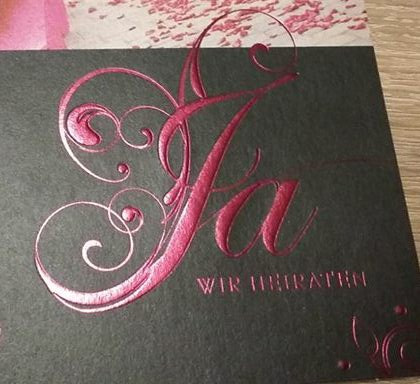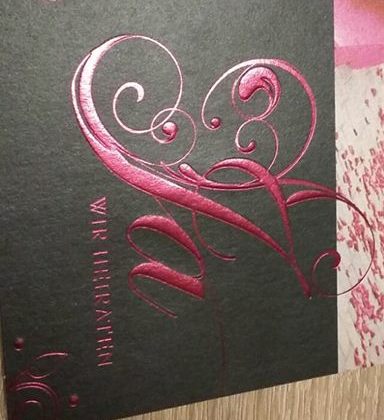
Welche Schrift? (ja, wir heiraten)
könnt Ihr mir bitte helfen, welche Schriftart dies ist.
Habe schon etliche Schriften durch, aber komme einfach nicht dahinter, wie diese Schrift heißt
Das J muss keiner Satzschrift entspringen, möglicherweise ist es auch als Zierbuchstabe für die Heißfolienprägung gestochen worden.
Kritik ist aber doch angesagt, und hier liegt das Problem in der Druckart der gesuchten Schrift, als metallic-Prägung.
Hier sollte man sich beim Fotografieren schon die Mühe machen, das die Schrift zum einen so beleuchtet ist, das die gesuchten Buchstaben auch erkennbar sind. Wenn man also nur irgendwo mal schnell ein Handybild schießen kann, kann es durchaus sein, das man das dann nicht erraten kann.
Und es geht in erster Linie um das  "J", nicht wie in der Überschrift steht (wir heiraten) --> hatte dies auch beim Beitrag reinstellen nicht dazugeschrieben.
dann bitte nächstes mal auch glech genau definieren, was vom Bild genau gesucht wird. So wie die Frage gestellt war, nahm ich an, es ginge um den ja schlecht erkennbaren Text "WIR HEIRATEN"
Ich habe ein bisschen gesucht, aber die Schrift nicht gefunden. Vor allem habe ich nach einem schlichteren J Ausschau gehalten, es könnte ja gut sein, dass die ganzen zusätzlichen Schnörkel per Hand hinzugefügt wurden. Am Ansatz der Rundung unten innen meine ich auch eine Ecke zu entdecken, die mich in dieser Ansicht unterstützt.